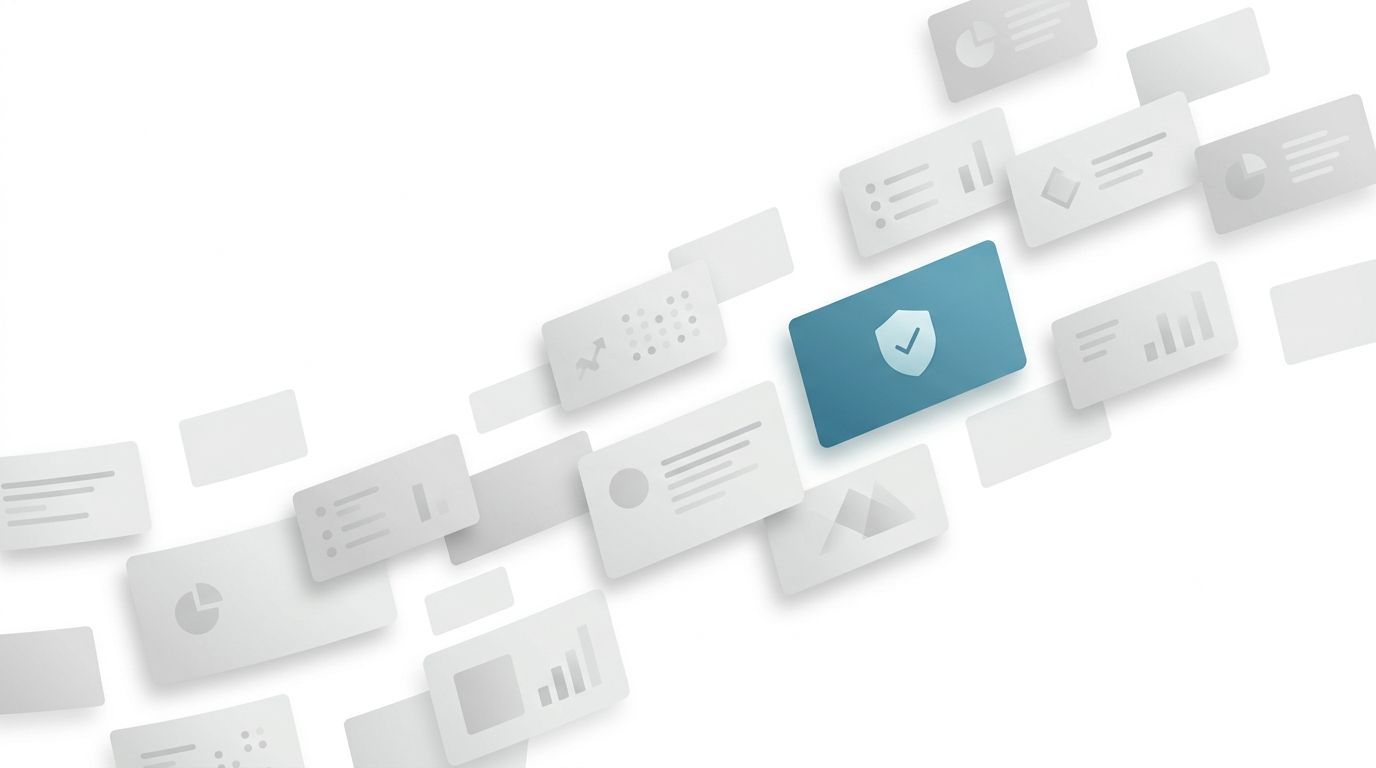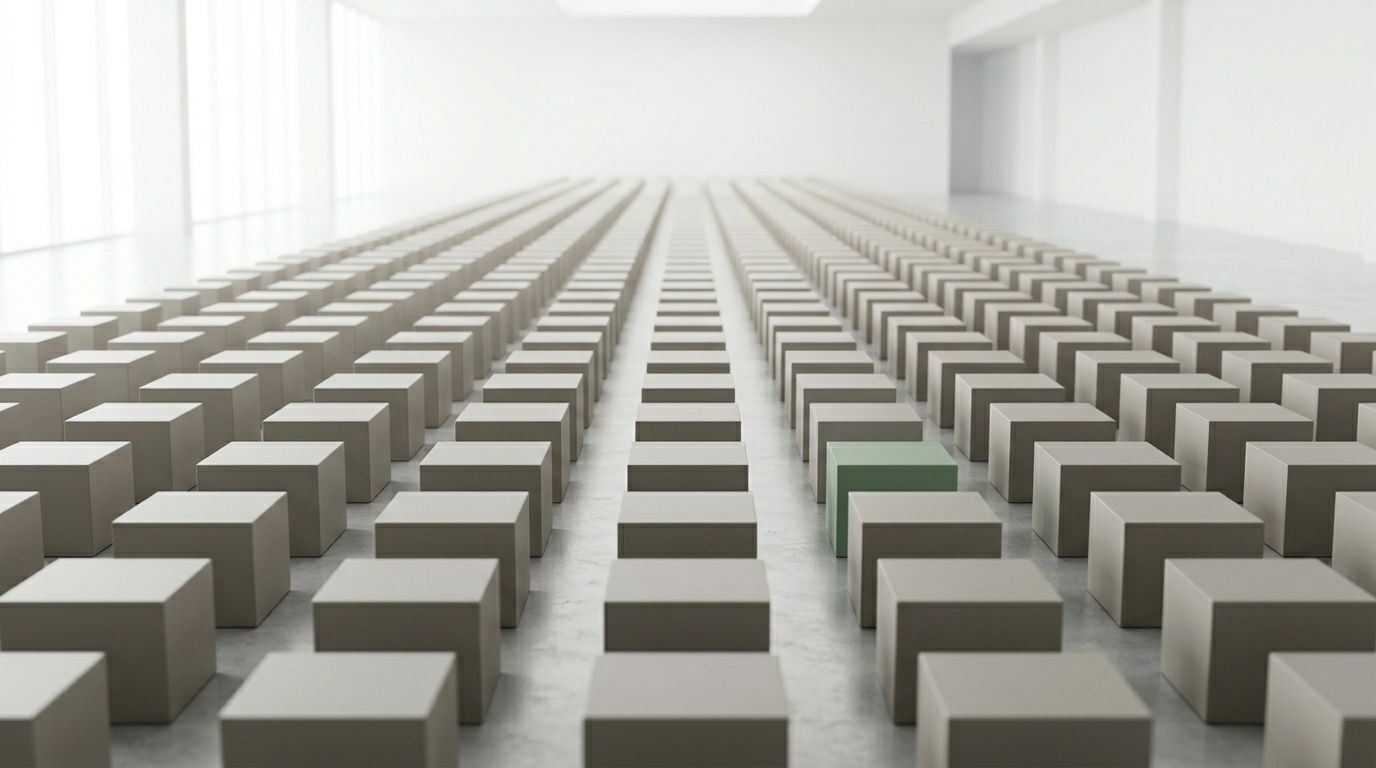
AI 让内容生产越来越快、越来越多,但企业也遇到了一个关键问题:在海量信息里,怎么让用户一直相信你的品牌?很多企业还在只靠故事和文案打造可信度,但在快节奏的环境里,视觉符号往往比文字更快被人记住、更快影响判断。在所有视觉元素里,字体远不只是好看不好看的问题,它直接帮助建立信任,影响用户对品牌是否靠谱、信息是否统一的整体感受。
AI 时代,品牌最缺的是可信度
研究早就证明,人们在还没认真读内容之前,就已经对品牌形成第一印象了。字体就是最早被大脑捕捉的信号之一,在你看懂文字之前,就已经决定了用户对你品牌的第一感觉。放到 AI 大量生成内容的今天,字体就是守住品牌可信度的关键。现在 AI 可以批量生产文案、海报、素材,但只有一套专属、统一的品牌字体,能给所有内容打上“官方认证”的烙印。坚持用独有的正版字体,就等于给内容贴了一个可信标签,让用户一眼分清哪些是官方可信信息,哪些是千篇一律的 AI 生成内容,哪些是虚假信息。
字体乱,可信度就打折扣
大型企业的品牌触点非常多,官网、APP、营销活动、社交媒体、投资者报告、客服界面、产品界面、数据看板等场景都要用到字体。一旦字体用得杂乱、随便替换、各处不统一,品牌形象就会碎片化。这不只是不好看,更会直接拉低品牌可信度。用户可能说不出哪里不对,但就是感觉“这个品牌不太靠谱”。字体混乱,传递的就是品牌不统一、不专业,而不统一,就是信任的杀手。
独特的字体,就是品牌可信度的第一道防线
市场竞争里,品牌拼的不只是你说什么,更在于用户能不能一眼认出你。研究显示,独特的品牌资产,能让用户更快记住你、优先选择你。Ehrenberg-Bass 研究所的 Byron Sharp 和 Jenni Romaniuk 也提出过核心观点:好认、不容易被混淆的品牌,才能真正跳出来。一套有辨识度的字体,只要坚持用,哪怕没有 LOGO、没有长篇文案,用户也能认出是你。我们看到几个字就认出大品牌,不是巧合,是长期统一用字体的结果。对企业来说,独特又统一的字体,就是别人抄不走的品牌壁垒,也是可信度的基础。
字体越统一,品牌越可信
很多人把统一当成设计要求,其实它是品牌管理问题。正如设计大师 Paul Rand 所说:信任不是靠新奇,是靠长期稳定、始终如一。不同部门、不同区域、不同合作方,如果都随便用字体、乱换字体,用户看到的品牌就是分裂的。授权过期、平台限制、随手替换……这些内部小问题,最终都会变成对外的“不靠谱”。一套统一的字体,传递给外界的信号很明确:专业、规范、注重细节、稳定可靠。反过来,字体杂乱,别人会下意识觉得这家公司管理混乱、不严谨,这对品牌可信度是致命的。
字体,必须升级为品牌战略资产
企业和品牌负责人,要像重视 LOGO、商标、口号一样,重视字体。真正出众的品牌,是一整套体系,而不是零散的素材。字体,是少有的能贯穿营销、产品、运营、管理所有场景的元素。想做好只需要:有清晰、标准的字体体系,能在全平台、全区域顺畅使用,有工具、模板和流程保证落地。当字体从“小事”变成战略资产,品牌才能真正掌控自己的形象,掌控用户的信任。
总结
品牌可信度,不是喊出来的,是在每一次曝光、每一次传播里,一点点积累出来的。品牌的本质,就是企业想表达的,和用户真实感受到的之间的距离,而字体,正在悄悄缩短这段距离。在内容随手可生成、信任越来越稀缺的今天,一套独特、统一、合规的字体,就是品牌可信度最稳定、最低成本的长期投资。字体不只是视觉,它直接决定:用户信不信你。